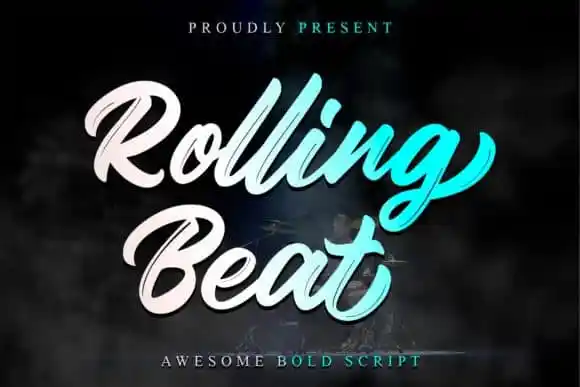
Rolling Beat Brush Font – Fonte Grátis
Rolling Beat Brush Font
A Rolling Beat Brush Font é uma elegante fonte script feita à mão com roupas desfeitas. Ela foi criada por um designer chamado Thomas Aradea e tem uma modularidade perfeita para designers de qualquer nível, desde novatos até aqueles que já têm experiência. Uma característica interessante da Rolling Beat Brush é sua fluidez ao escrever à mão, que lhe dá um toque elegante perfeito para seus projetos favoritos. Esta fonte tem uma aparência surpreendentemente distinta e eterna, tornando-a perfeita para aqueles desejando adicionar um toque único a seus designs. Ela é especialmente adequada aos criativos que buscam personalizar suas tipografias existentes ou criar novos projetos. A Rolling Beat Brush Font não apenas trará vida às suas criações, mas também fará você cair de amores por sua originalidade única e seu estilo eterno. Sua versão Script é uma escolha ideal para qualquer designer que deseja adicionar um toque especial aos seus trabalhos gráficos, sejam eles em designs de revistas, logotipos ou até mesmo em artesanato. Não perca tempo e dê à sua obra o toque diferenciado que ela merece. Descubra por si mesmo como a Rolling Beat Brush Font pode transformar seu trabalho no campo da design gráfico para melhor!